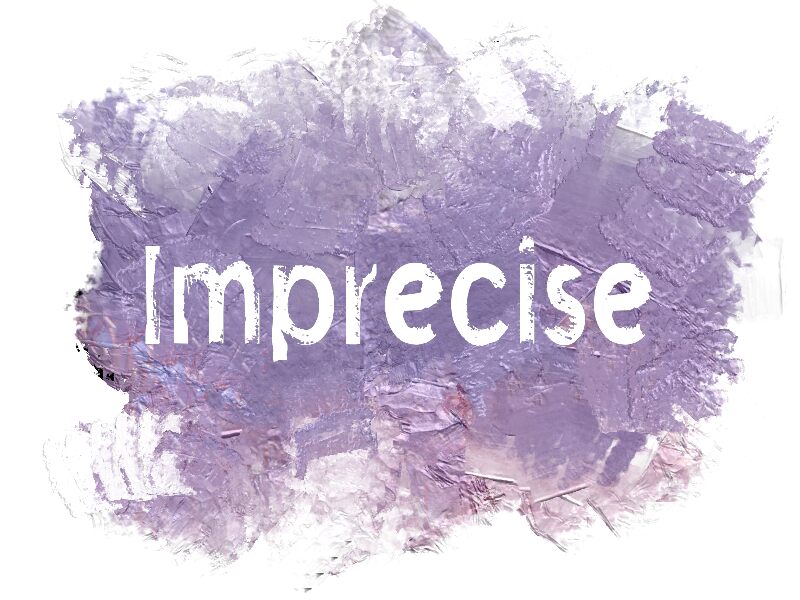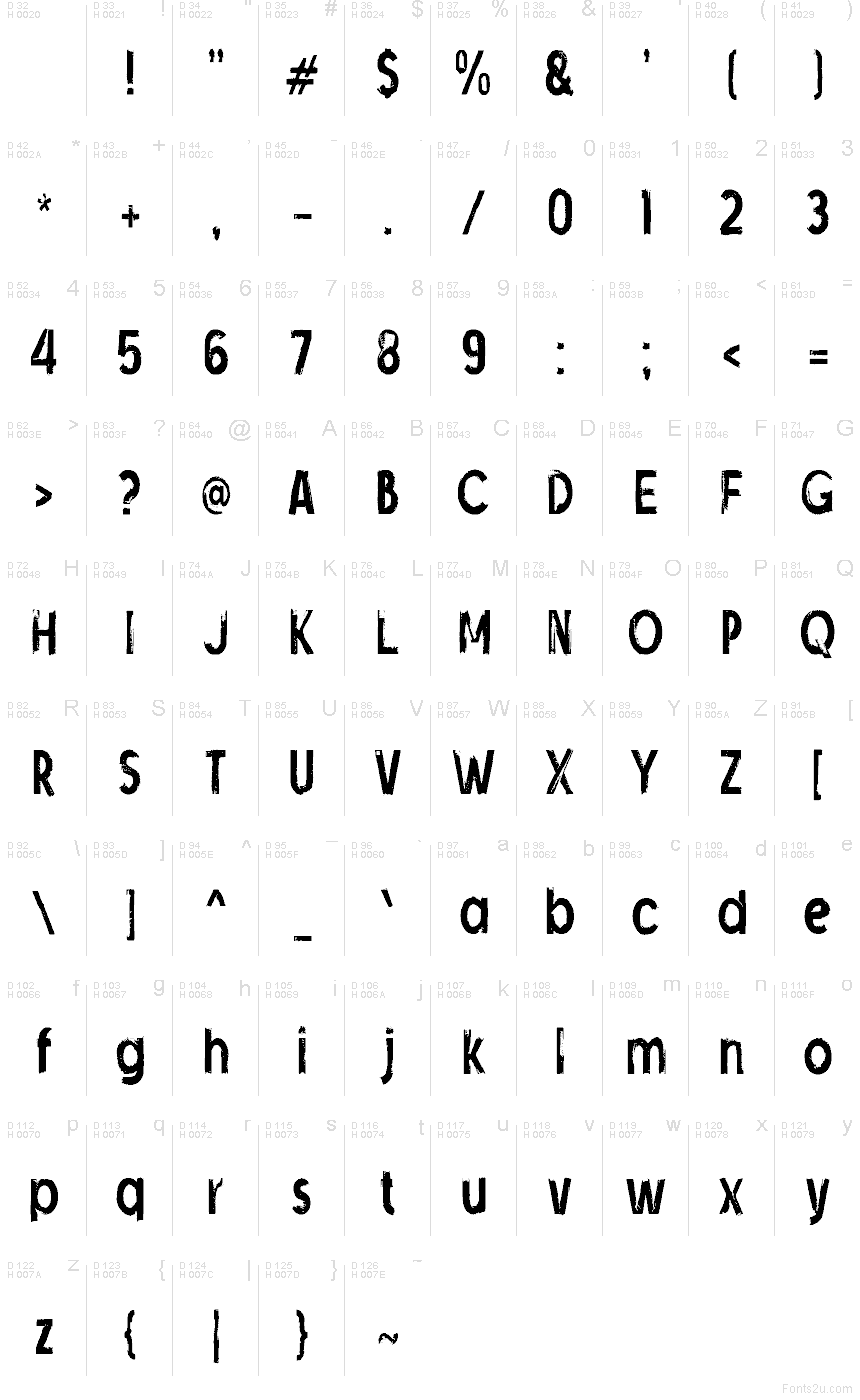
Imprecise
Imprecise od Wep je bezplatné displejové písmo charakteristické drsnou, akoby zoškrabanou štruktúrou namiesto úhľadných obrysov. Písmená si zachovávajú svoju solídnu tmavú hmotu, no vďaka opakujúcim sa vrypom, šmuhám a opotrebovaným okrajom pôsobí celý dizajn dojmom, ako by bol vytlačený, zostarnutý a ošľahaný, nie precízne dokončený.
Toto poškodenie povrchu dodáva krátkym nadpisom, plagátom, obalom albumov, hororovým letákom a grafike v štýle grunge ostrejší výraz bez potreby ďalších efektov. Skvele sa hodí aj na promo na sociálne siete a obálky podujatí, kde táto narušená štruktúra sama o sebe dokáže vytvoriť vizuálny dojem opotrebovania, veku alebo šumu.